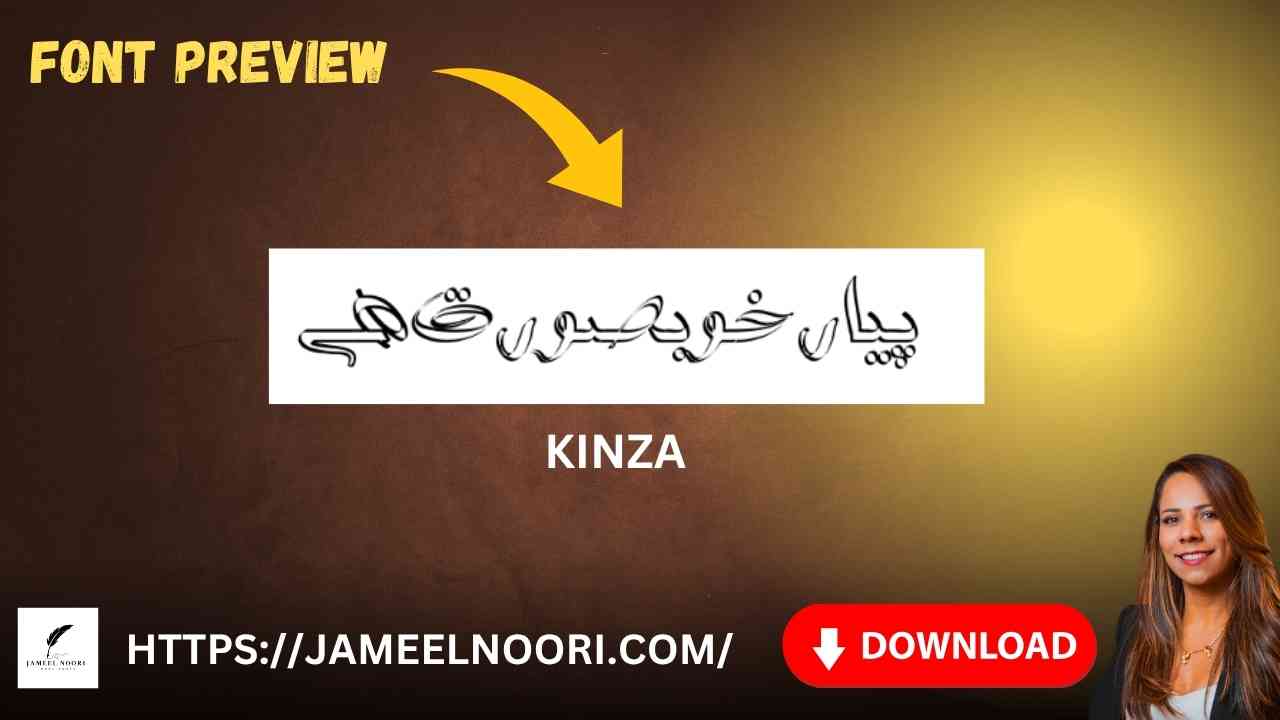
Introduction of Download Urdu Font Kinza
Agar aap Urdu typing ke liye ek beautiful aur easy-to-read font search kar rahe hain, to Download Urdu Font Kinza aapke liye perfect choice hai. Ye ek TrueType Font (TTF) hai jo Windows, Mac, aur Linux par smoothly work karta hai.
Features of Download Urdu Font Kinza
Download Urdu Font Kinza ke kuch top features ye hain:
- ✅ Smooth and elegant Urdu typography
Why Choose Download Urdu Font Kinza for Urdu Projects
Download Urdu Font Kinza ka use karne ke kuch reasons:
- Elegant design – Professional documents aur certificates ke liye best
- High readability – Long Urdu text me bhi clear visibility
Agar aap Urdu writing me ek elegant aur modern look chahte hain, to Download Urdu Font Kinza best option hai. Iska professional design, compatibility aur high rating isay Pakistan me designers, students, aur bloggers ka favourite banata hai. Download karein aur apne projects me professional touch add karein.
Can I use Kinza font for logo design?
Yes, its stylish design makes it great for logos.
Does Kinza font include all Urdu characters?
Yes, it contains all standard Urdu alphabets and numerals.
Is Kinza font suitable for calligraphy projects?
Yes, it is perfect for Urdu calligraphy and artistic projects